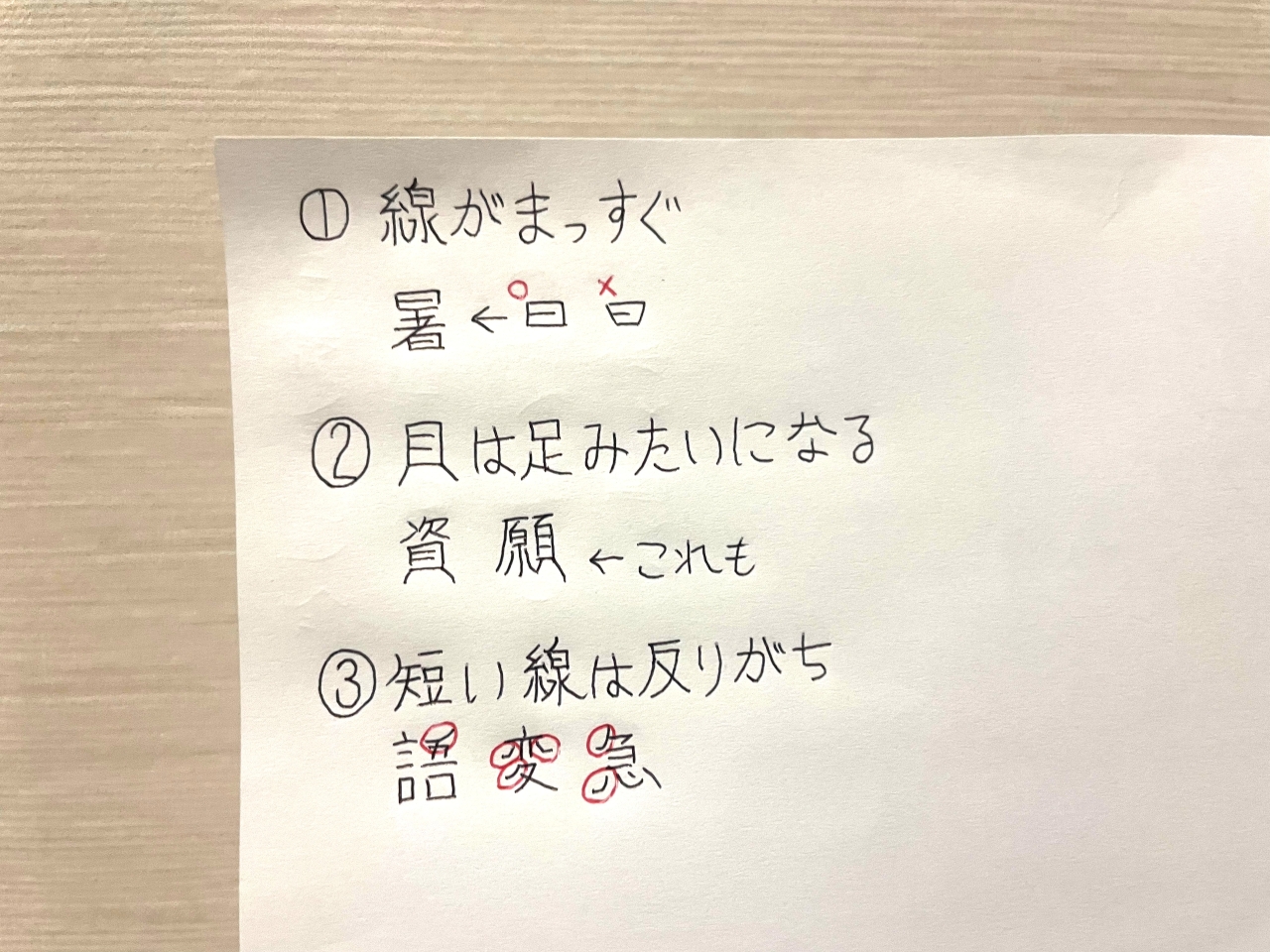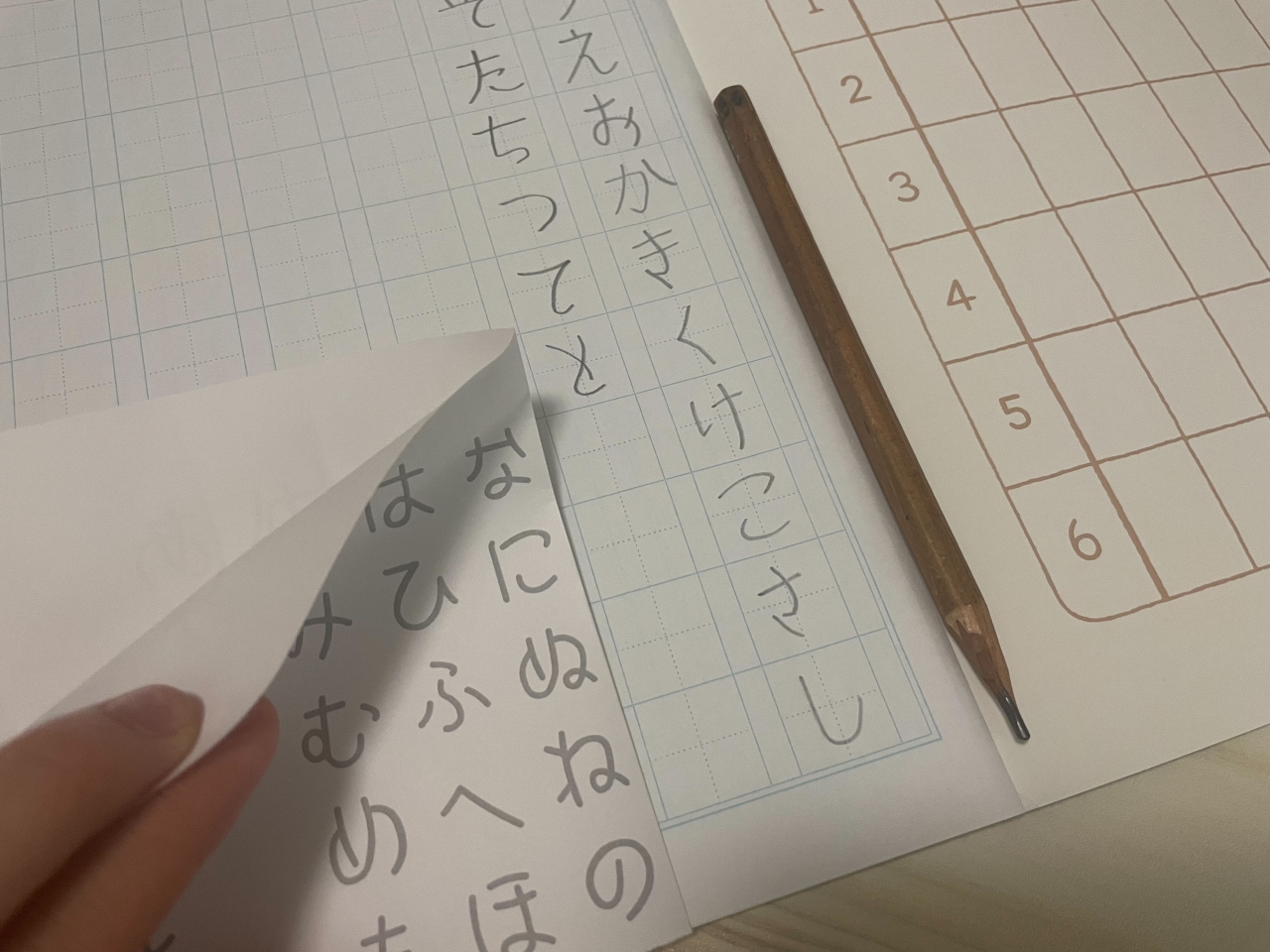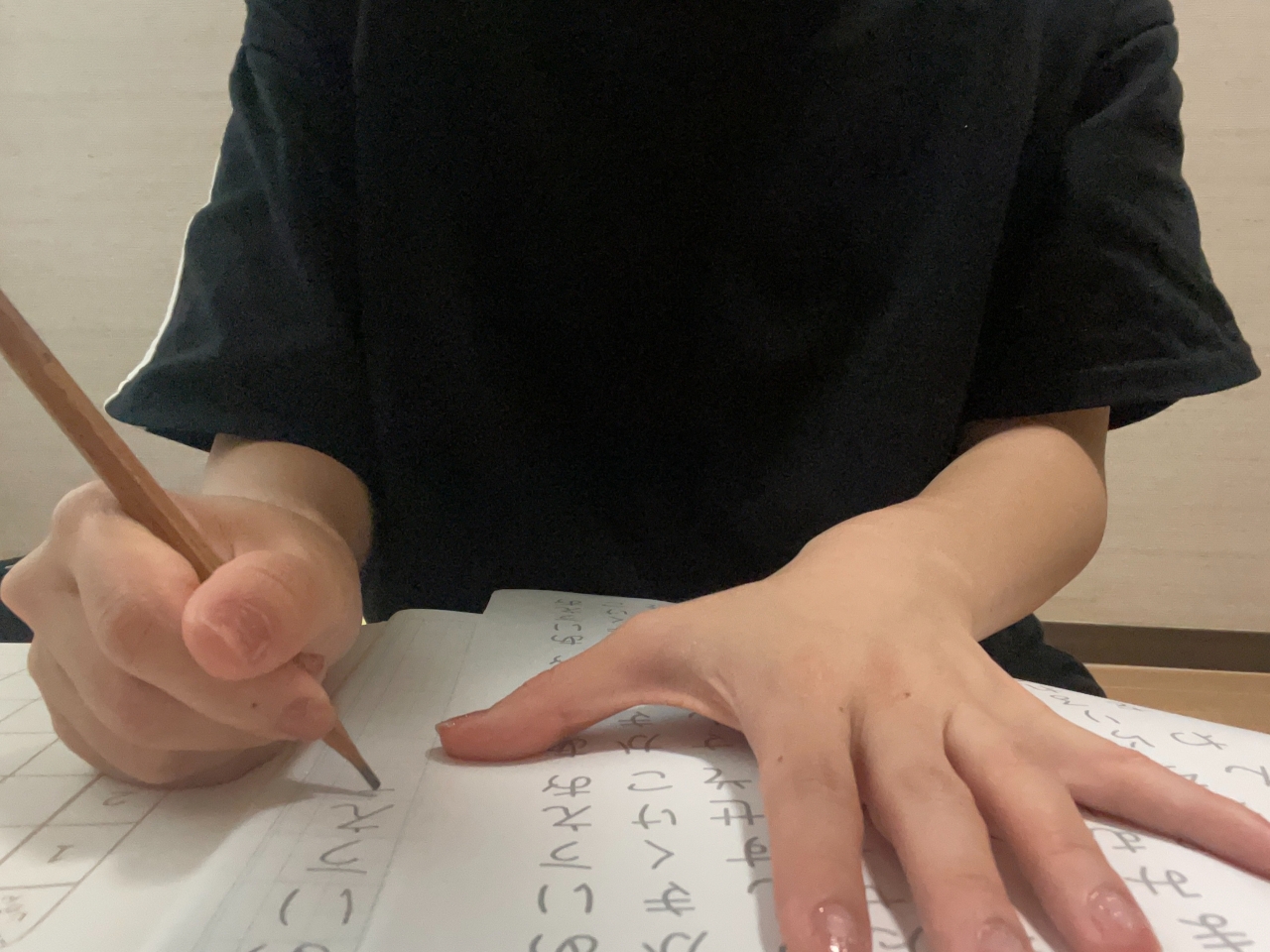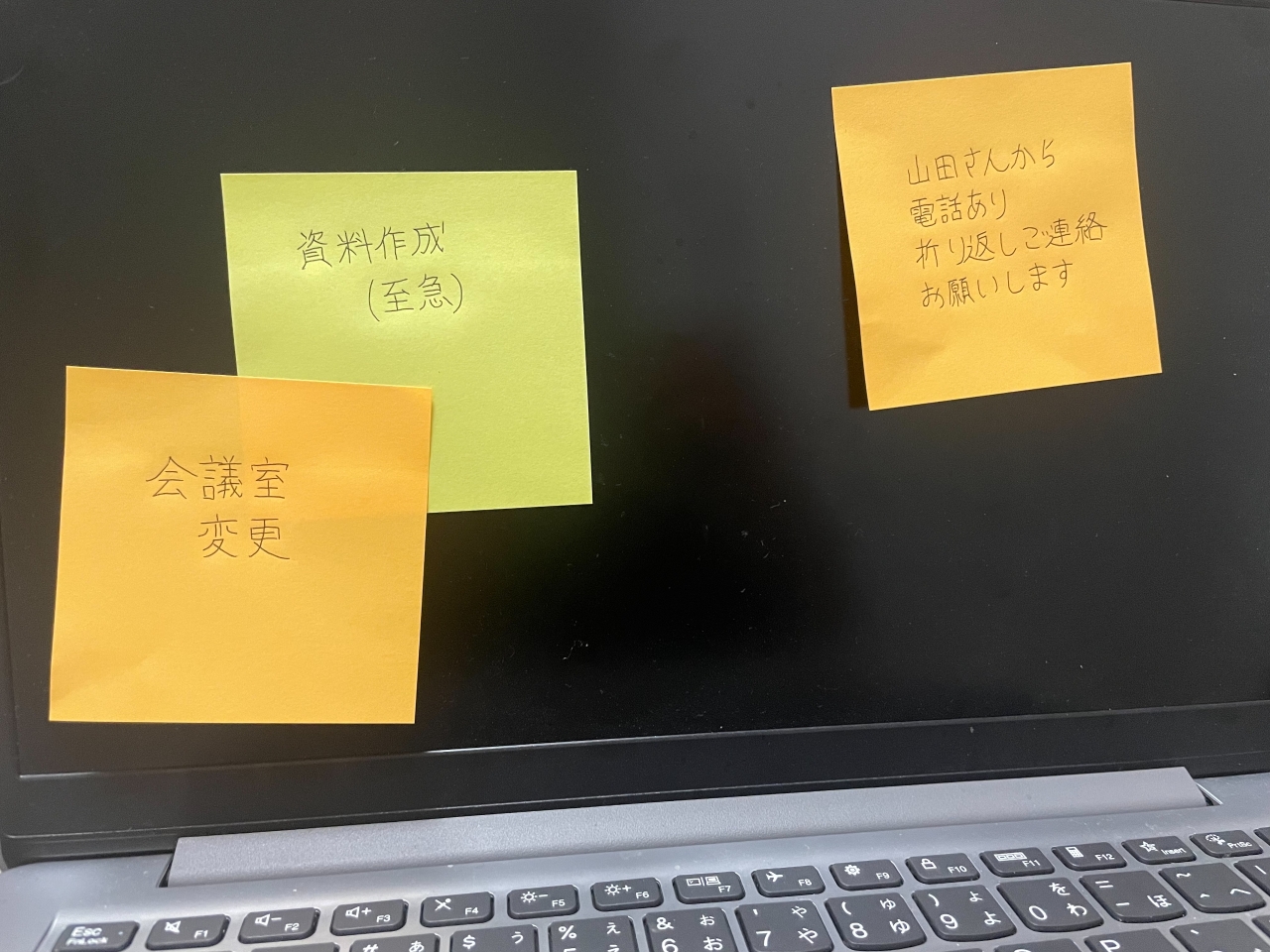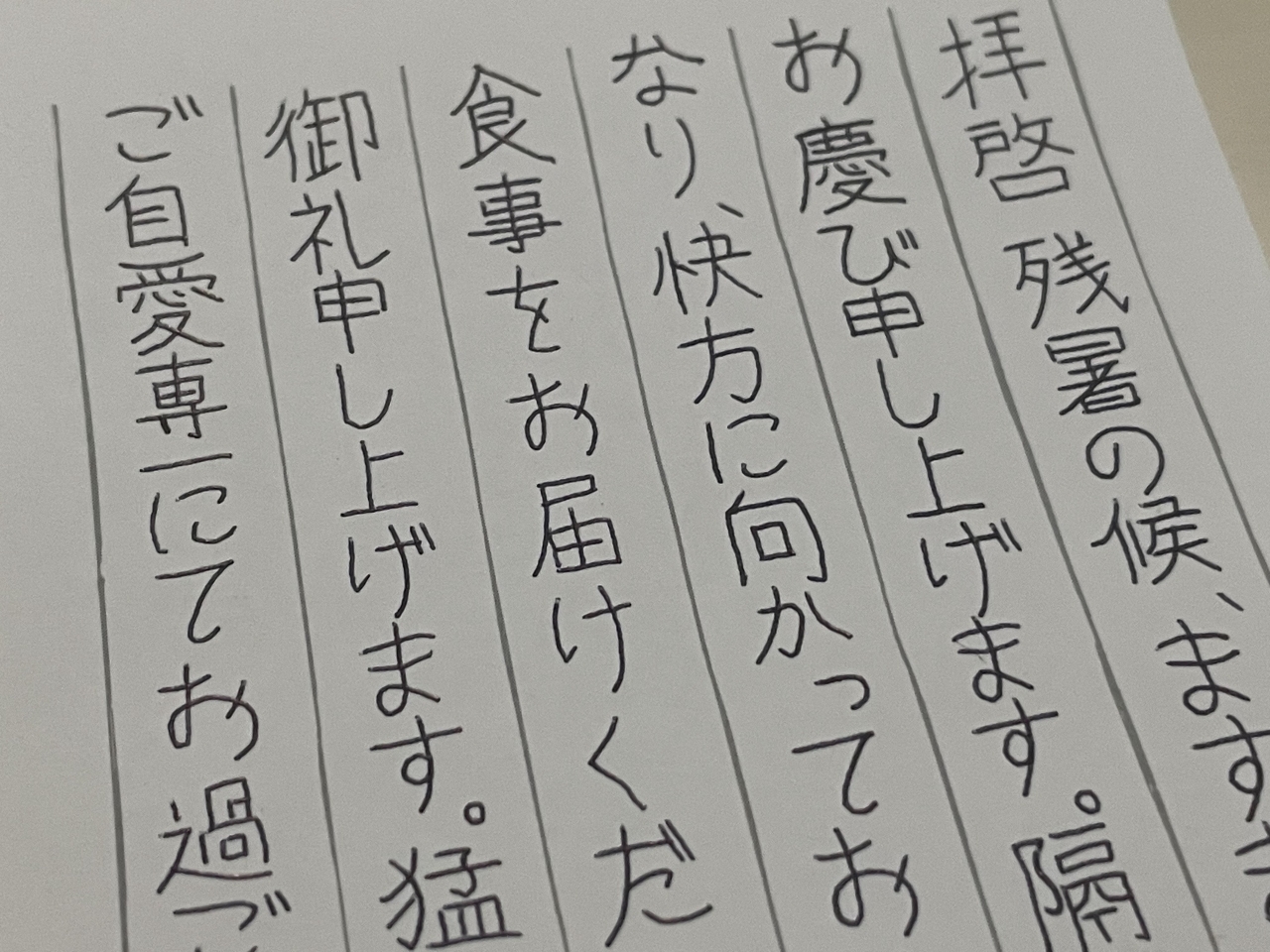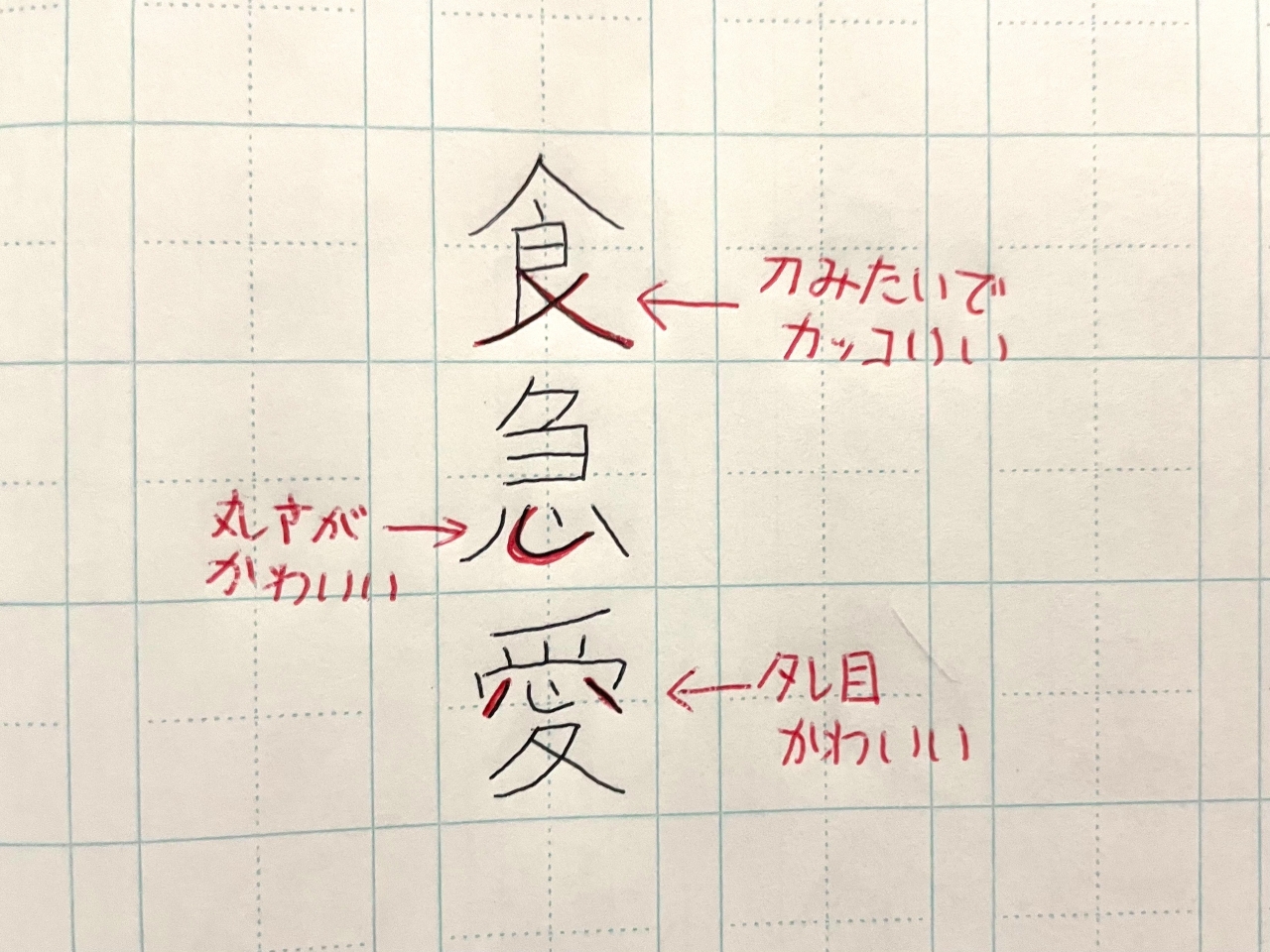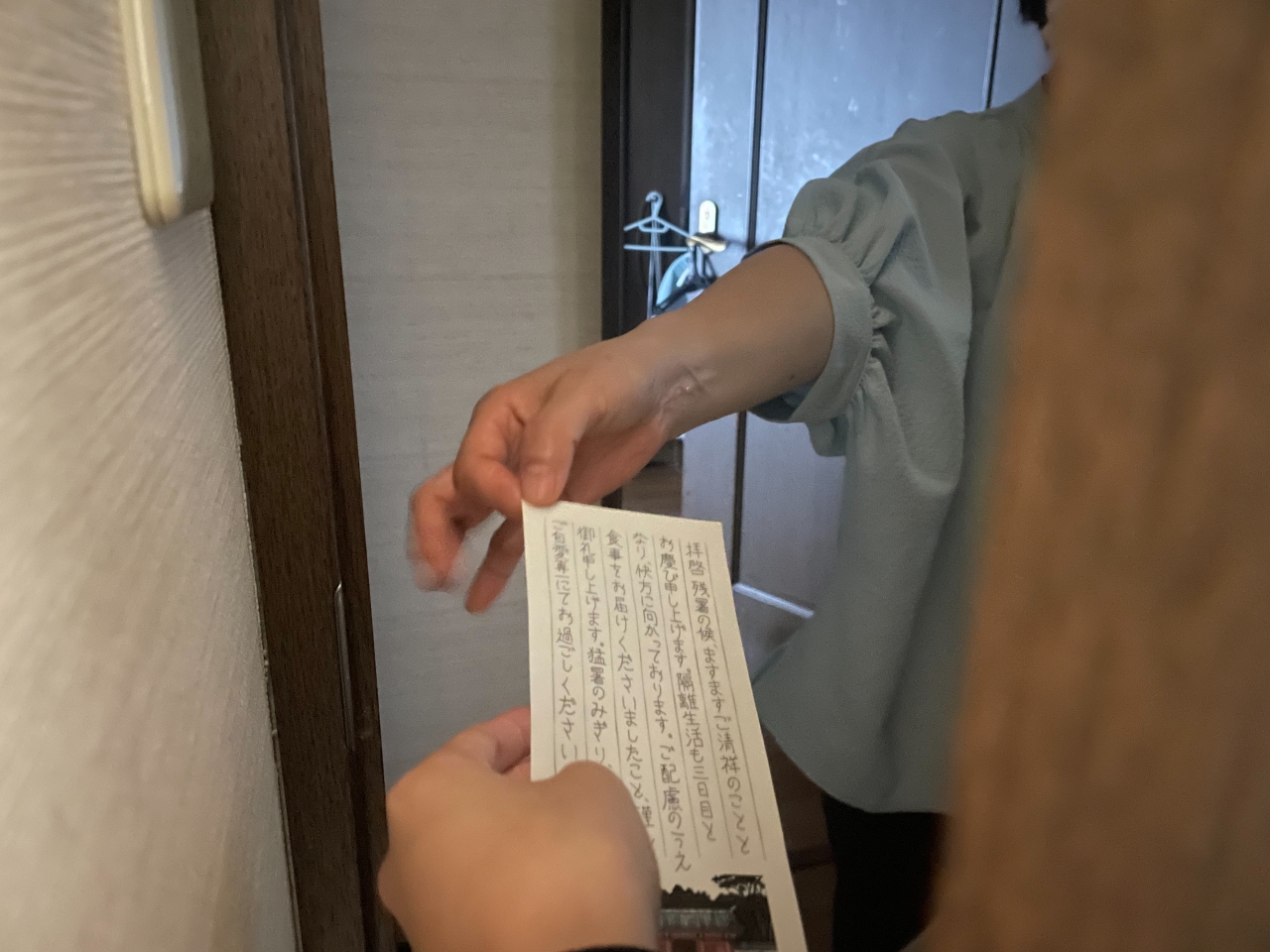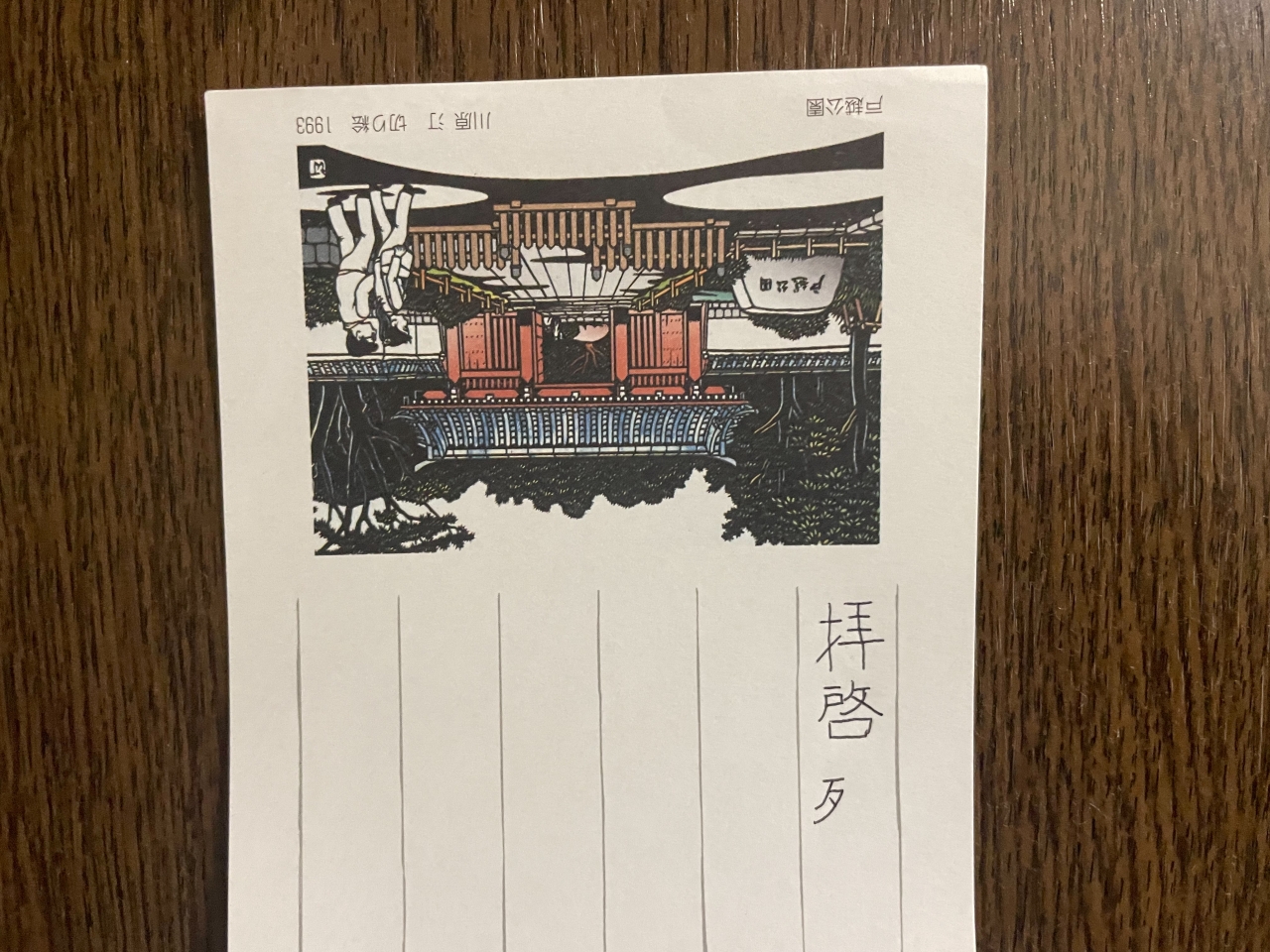
フォントは声色を表している気がする
フォントを変えると、文章が脳内で読み上げられる声色が変わるように思える。しねきゃぷしょんはどんな内容でもセリフっぽい声になる気がして面白い。
自分の声をフォントで例えたら何になるのか気になってきました。しねきゃぷしょんで喋れるようになりたいなぁ。
「しねきゃぷしょん」をご存知でしょうか。映画の字幕をもとにした独特の柔らかさのあるフォントです。
さりげなくスラスラっと書いた字がしねきゃぷしょんだったらさぞかっこよかろう!ペン習字の要領でしねきゃぷしょんと向き合い、たくさん書いてみました。
小学生の時、字が汚かったので習字教室に通っていた。
そこでは筆で書く”毛筆”のほかに、鉛筆で書く”硬筆”も習っていた。どちらも先生が書いた綺麗な字をひたすら真似るスタイルで、特に硬筆においては先生の字の癖がかなりうつった自覚がある。今も自分の字に残っている。
つまり手本の字を真似し続けると、その字の形や癖が染みつくのだ。字を矯正したい大人に人気の「ペン習字」もその要領である。
ということは、独特の雰囲気を持つこのフォントに矯正することだってできるのでは?その名も「しねきゃぷしょん」。
”シネ”の名のとおり、映画(シネマ)の字幕風のフォントです。実際に映画の字幕のデータから作られたそう。味があって好きなんですよね。それに線の太さを変えなくてよいのでボールペンで再現しやすそう。
まずは今の自分の字としねきゃぷしょんとの違いを見てみた。青字がお手本のしねきゃぷしょん、黒字が普段どおり書いた自分の字、赤字がお手本に合わせて修正したものです。
じっくり観察してみると、特徴が顕著なグループが3つあることに気づいた。これらをおさえるだけでかなり雰囲気が出そう。
とりあえず、お手本の字をなぞって矯正してみよう。
こうして字をなぞっていると習字教室を思い出すなぁ。ギャルみたいな先生で、ギャルみたいな口調で字を直された。お元気だろうか。
ひととおりなぞって練習したら、あとはひたすら書きまくります。
実はこの企画を始めた数日後、コロナウイルスを発症した。帰省していたため、実家の一室に独房のように隔離される生活の幕開けである。今週の記事をこの企画にしておいてよかった~。家を出ずにできるしいい暇つぶしになるぞ!
外出できないので、親に頼み込みジャポニカ学習帳を買ってきてもらった。25にもなって親にノートを買ってもらうとは思わなかった。
漢字を含めるとキリがないので、字をよく書くシチュエーションである「仕事の伝言」「手紙」で書く文を決め、そこに出てくる漢字にヤマを張って練習した。
書きまくっていると、漢字の形にも特徴があることに気づいた。縦と横の線は基本的にまっすぐで、貝の下は足みたいになっていて、短い線は反りがち。これらをおさえると、お手本がない漢字でも少なくとも「しねきゃぷしょん風」に書けるぞ。
今やもうチャットで伝言することがほとんどだろうが、ここでは手書きのぬくもりを感じていただきたい。フォントだけど。
「しねきゃぷしょんっぽさ」は書く文章の内容にも左右されるようだ。ビジネスシーンにしねきゃぷしょんを持ち込みたかったら、洋画の翻訳風にちょっとオーバーな言い回しで書くことをおすすめします。
手書き文字といえば手紙だろう。コロナ患者の私に食事を届けてくれる母に感謝の手紙をしねきゃぷしょんでしたためた。さながら独房からの手紙である。
おお、しねきゃぷしょんだ!我ながらかなりしねきゃぷしょんだ。印刷したみたい。
手書き用の一筆箋が、印刷みたいに均一な文字で埋められているのは少し不気味な気もするな。
さっそく帰宅した母に渡した。
しねきゃぷしょんの手紙を渡された感想を尋ねたら特になしと言われた。何かあってくれよ。
フォントを変えると、文章が脳内で読み上げられる声色が変わるように思える。しねきゃぷしょんはどんな内容でもセリフっぽい声になる気がして面白い。
自分の声をフォントで例えたら何になるのか気になってきました。しねきゃぷしょんで喋れるようになりたいなぁ。